Letras para Free Fire ⚡ Nombres y Nick para Copiar y Pegar
En Free Fire, el lobby ya es campo de batalla — y tu nick es lo primero que el enemigo ve antes de que empiece la partida. Un nombre con Tipos de letras y letras especiales bien elegidas comunica actitud, experiencia y estilo desde el primer segundo.
Con el generador de letras para Free Fire de tiposletras.com puedes crear un nick con letras góticas, letras chinas, símbolos y estilos únicos listos para copiar y pegar en segundos. Sin apps, sin registro — funciona directo desde el navegador en Android, iPhone y emuladores.
Millones de jugadores en LATAM ya personalizan sus nicks con letras especiales para destacar en clasificatoria, representar a su clan o simplemente intimidar antes de que empiece el juego. Y si quieres llevar ese estilo más allá del juego, también puedes usar nuestras letras bonitas para Instagram y personalizar tu perfil completo.
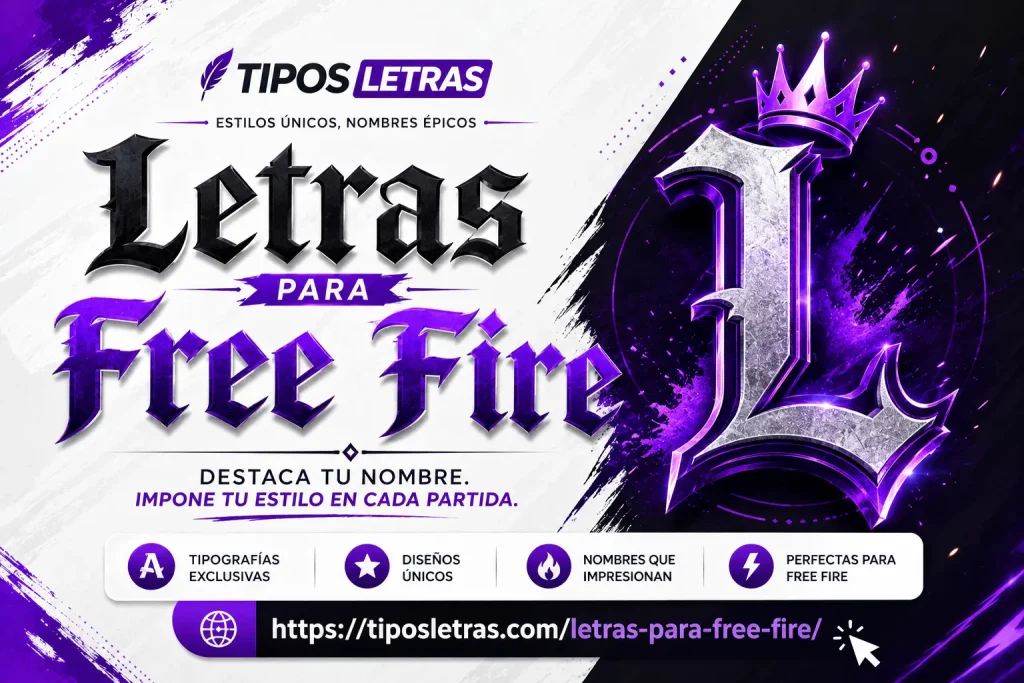
Cómo usar el generador de letras para Free Fire
Crear un nick personalizado para FF toma menos de 30 segundos:
Escribe tu nombre o apodo en el generador.
Explora los estilos disponibles automáticamente.
Elige el diseño que más te guste.
Presiona el botón copiar.
Abre Free Fire y pega el nick en tu perfil.
Consejo:
Los nombres cortos suelen verse mejor dentro del juego porque son más fáciles de leer durante las partidas rápidas.
Tipos de letras para Free Fire
Letras Góticas para Free Fire 💀
Las letras góticas son el estilo más usado por la comunidad competitiva de Free Fire dentro de las letras para Free Fire. Su origen en la tipografía medieval Fraktur les da ese aspecto oscuro y poderoso que intimida desde el lobby. Son perfectas para jugadores que buscan transmitir experiencia y actitud dentro del juego.
Tip:
En pantallas pequeñas de móvil, las góticas se leen mejor cuando el nombre tiene menos de 8 caracteres.
Letras Chinas para Free Fire ㄥ乇ㄒ尺卂丂
Las letras chinas en Free Fire no son caracteres del idioma chino real son símbolos Unicode que visualmente imitan esa estética asiática. Crean un efecto único que muy pocos jugadores usan, lo que hace que tu nick sea inmediatamente reconocible entre cientos de usuarios.
Tip:
Combina una o dos letras chinas con tu nombre normal para un efecto más equilibrado y legible en el campo de batalla.
Letras Egipcias y Griegas
Este estilo mezcla caracteres del alfabeto griego y símbolos de inspiración egipcia para crear nombres con un aire misterioso y antiguo dentro de las letras para Free Fire. Son populares entre jugadores que buscan un nick diferente, alejado de los estilos más comunes dentro del juego.
Letras Pequeñas para nick FF
Las letras pequeñas o minúsculas especiales son ideales porque ocupan menos espacio visual dentro del límite de 12 caracteres. Esto permite agregar más elementos decorativos como símbolos o marcos sin sacrificar el nombre completo.
Tip:
Las letras chiquitas funcionan muy bien como sufijo por ejemplo: DARK ᵏⁱˡˡᵉʳ
Letras Raras y Modificadas
Las letras raras combinan caracteres Unicode poco conocidos que la mayoría de jugadores nunca ha visto dentro de las letras para Free Fire. Este tipo de fuente hace que tu nick sea prácticamente imposible de imitar, lo que es una ventaja real en servidores con ranking donde la identidad importa.
Símbolos para Nick de Free Fire
Los símbolos son el elemento decorativo que transforma un nombre ordinario en un nick memorable. En Free Fire, los símbolos compatibles con Unicode aparecen correctamente en Android, iOS y emuladores sin ningún problema.
Tip pro:
Los marcos ꧁꧂ consumen 1 carácter cada uno. Planifica tu nick contando todos los elementos antes de pegarlo en el juego.
Símbolo Invisible y Espacio para Free Fire
El carácter invisible es uno de los trucos más buscados por la comunidad de FF. Permite crear la ilusión de un nombre vacío o agregar espacios entre palabras donde normalmente el juego no lo permite.
Cómo usarlo:
- Copia el carácter de arriba
- Pégalo entre las palabras de tu nick
- También puedes usarlo como nombre completo para el efecto de nombre invisible
Tip:
Garena puede actualizar sus filtros en cualquier momento. Si el carácter invisible deja de funcionar, es porque el juego bloqueó ese símbolo específico en una actualización reciente.
50 Nombres para Free Fire — Listos para Copiar
Elegir un buen nombre es tan importante como el estilo de letra que uses. Un nick efectivo debe ser corto, memorable y visualmente impactante. Aquí tienes una selección completa organizada por categorías para que encuentres el que mejor te represente.
Nombres para Free Fire de Hombre 👑
20 Nombres para Free Fire Originales
Con el generador de tiposletras.com tienes acceso a cientos de estilos gratuitos de letras para Free Fire, desde góticas intimidantes hasta letras chinas únicas, todo listo para copiar y pegar en segundos. No necesitas instalar ninguna aplicación ni crear una cuenta para empezar.